ใกล้เข้าสู่ช่วงตรุษจีนปี 2023 แล้ว สร้างบรรยากาศต้อนรับปีใหม่จีนกันหน่อย ด้วยฟอนต์จีนสำหรับภาษาไทยสวย ๆ จากเว็บไซต์ ฟอนต์.com เผื่อว่าใครจะนำไปตกแต่งกราฟิกสำหรับอวยพรวันตรุษจีน
9 ฟอนต์จีน สวย ๆ ตกแต่งคำอวยพร ต้อนรับตรุษจีนปี 2023
1. หมูย่าง (MN Muyang)
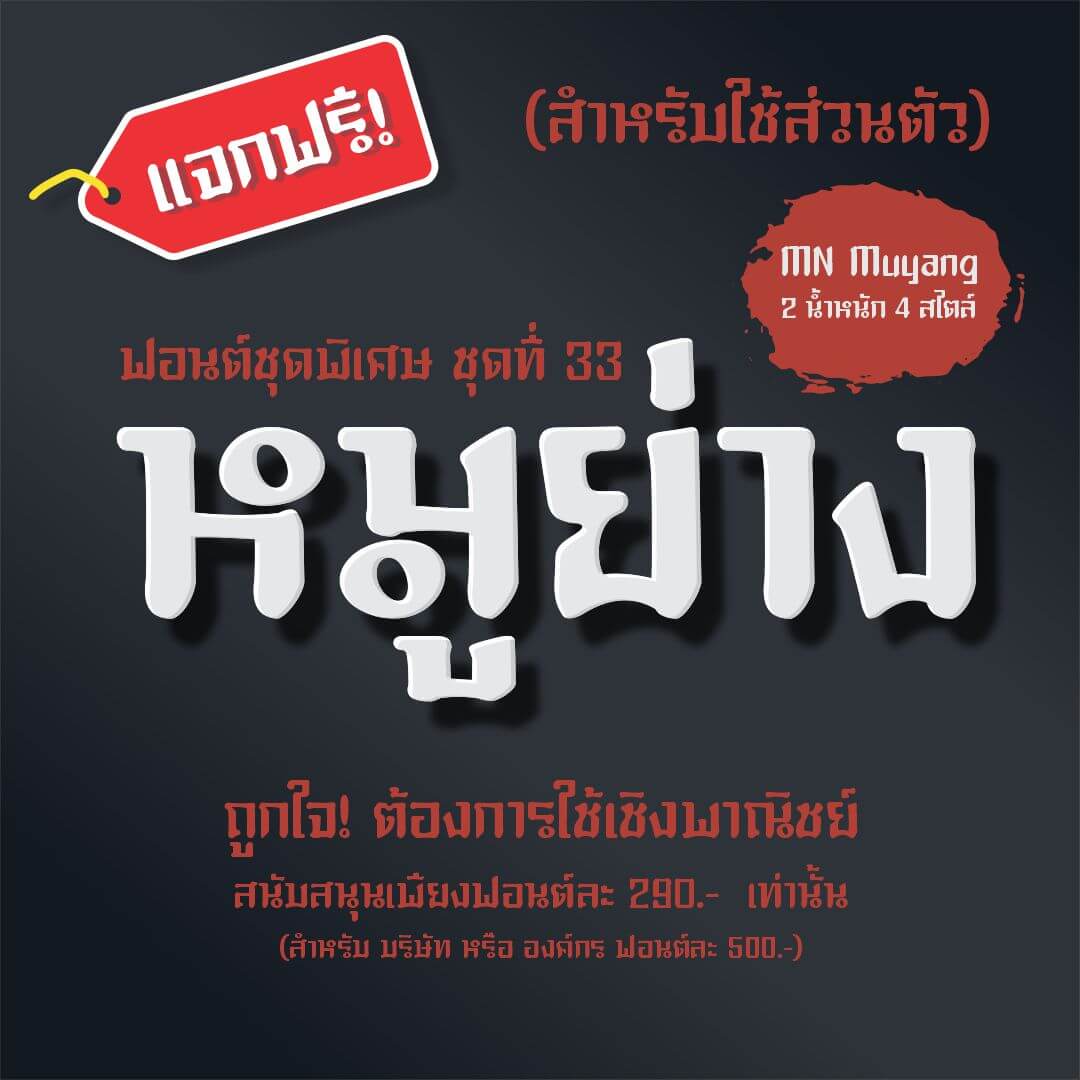
2. เสี่ยวหลงเปา (MN XIAO LONG PAO)
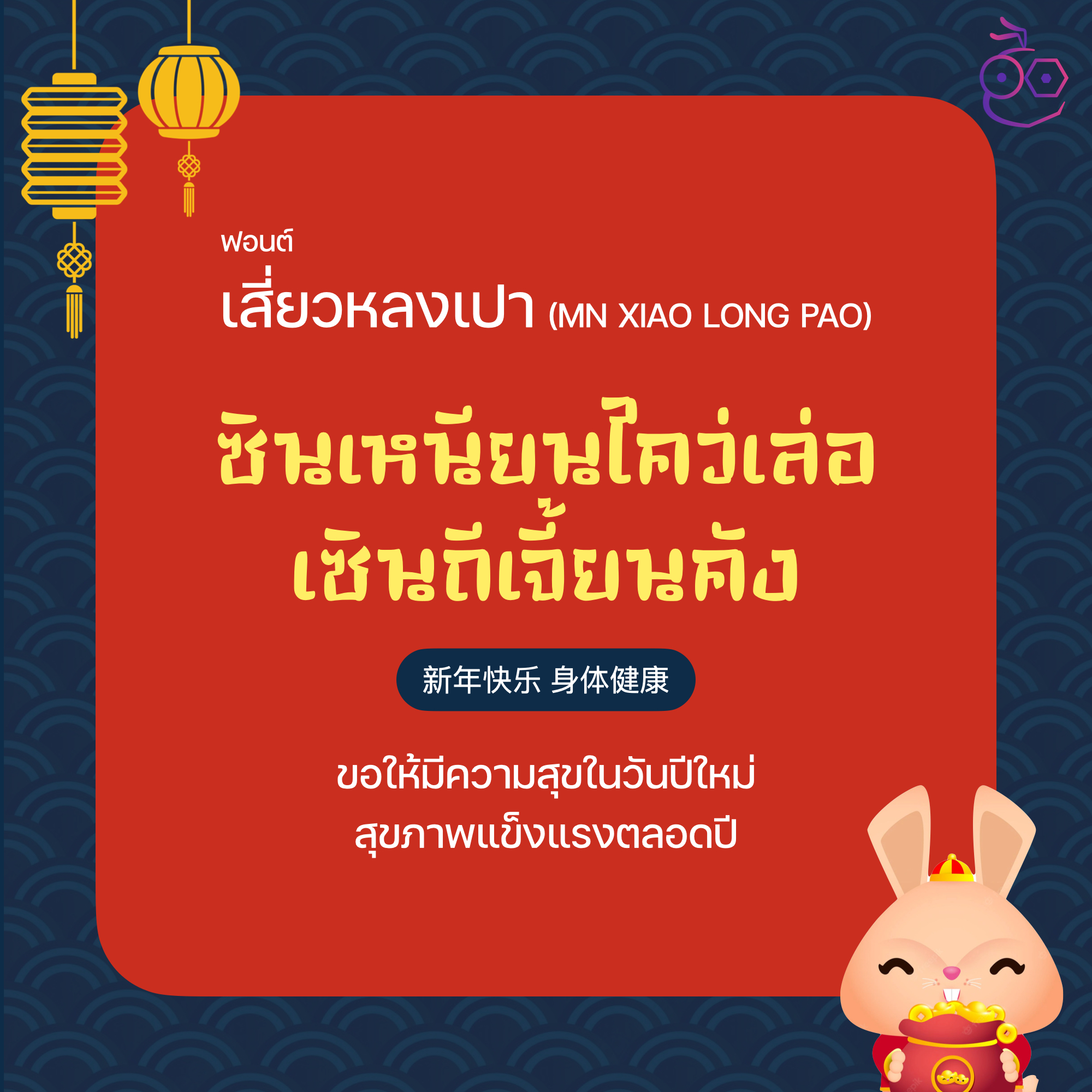
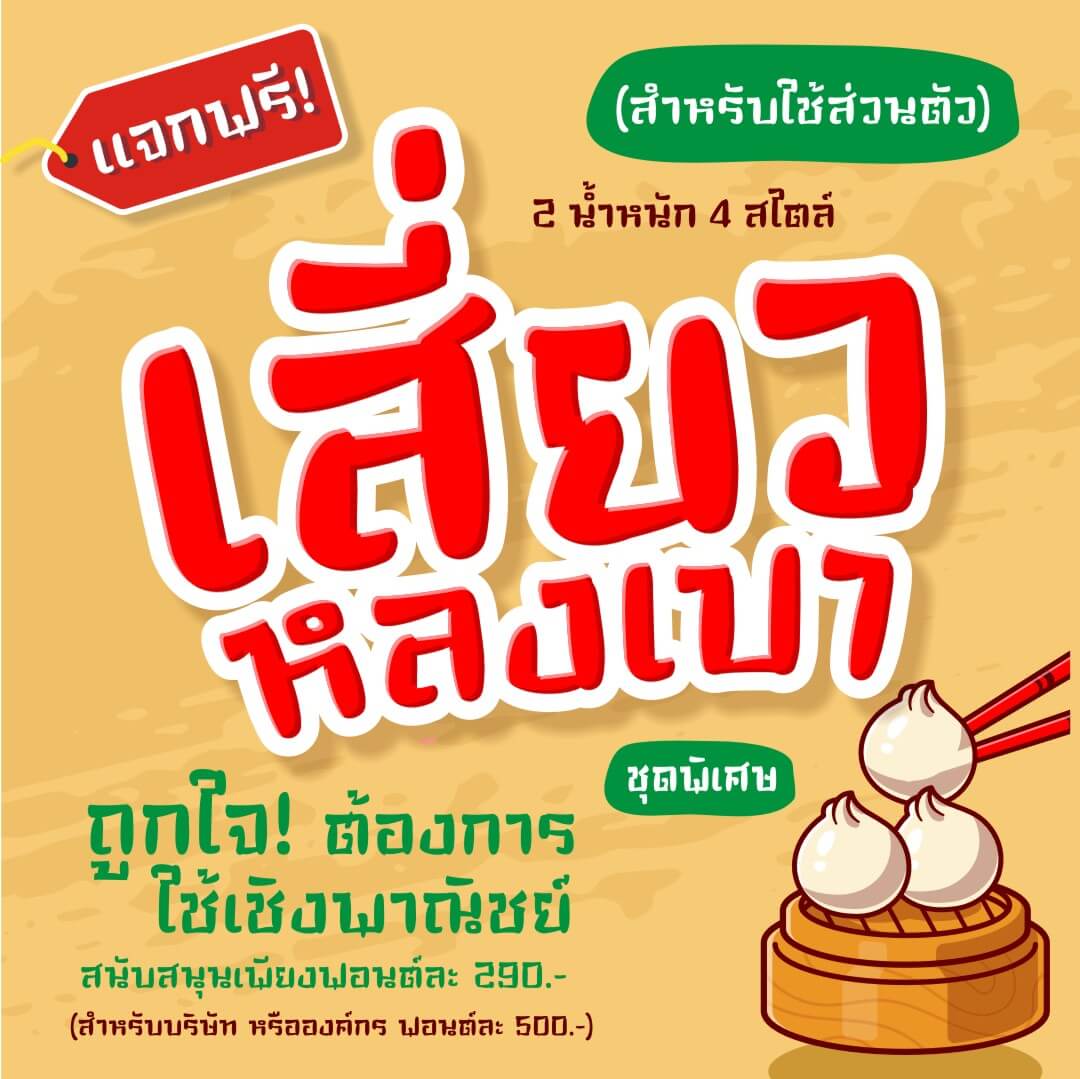
3. ติ่มซำ (Dimsum)
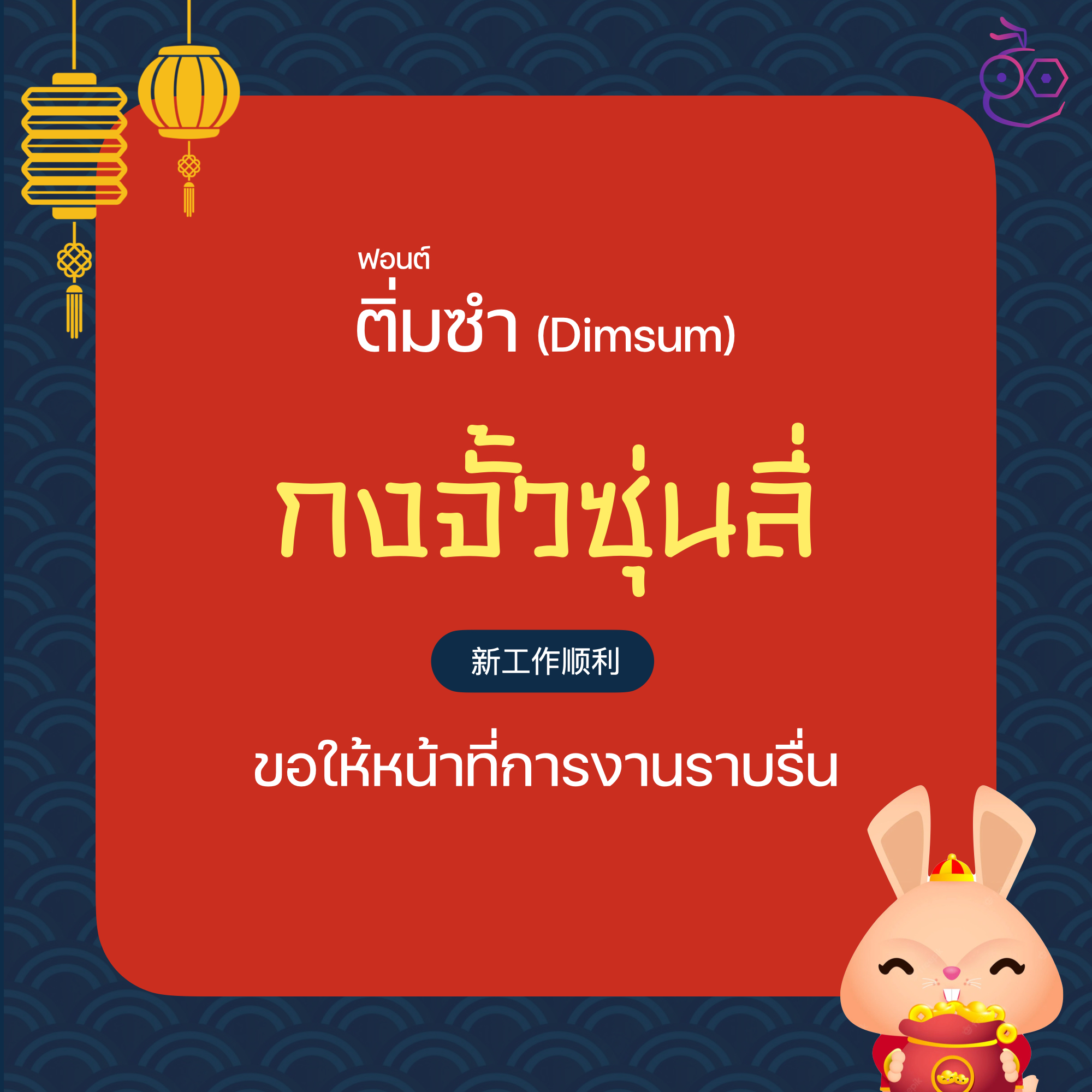
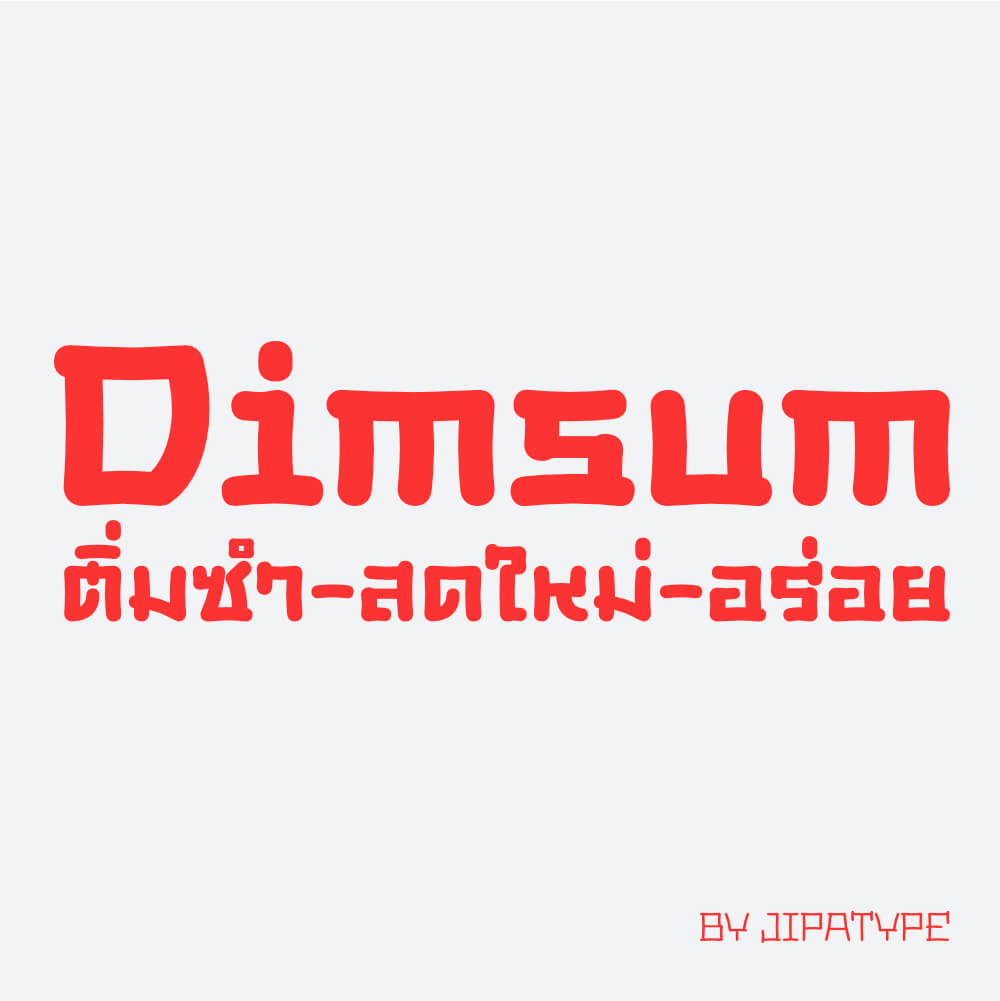
4. ฟอนต์ซาลาเปา
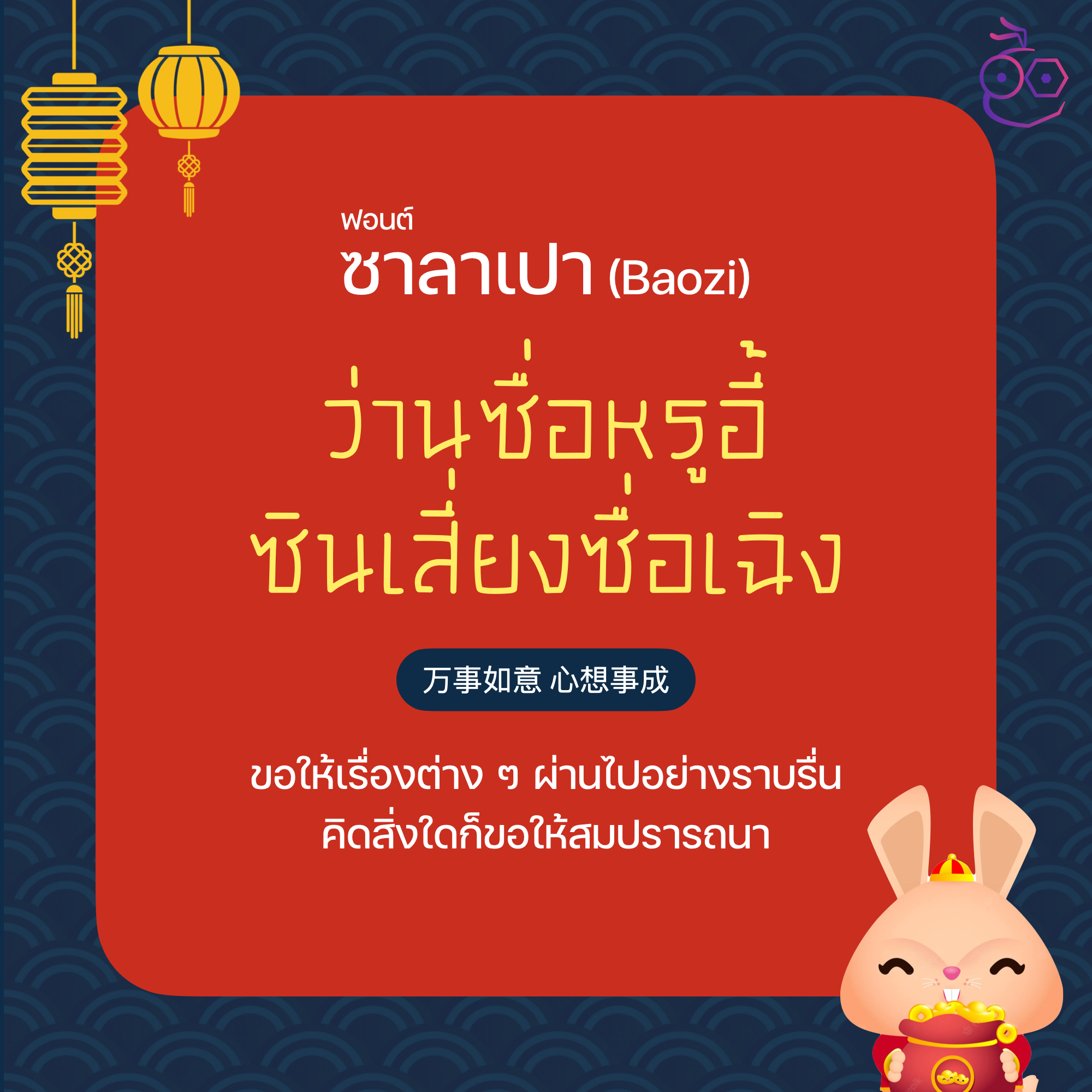
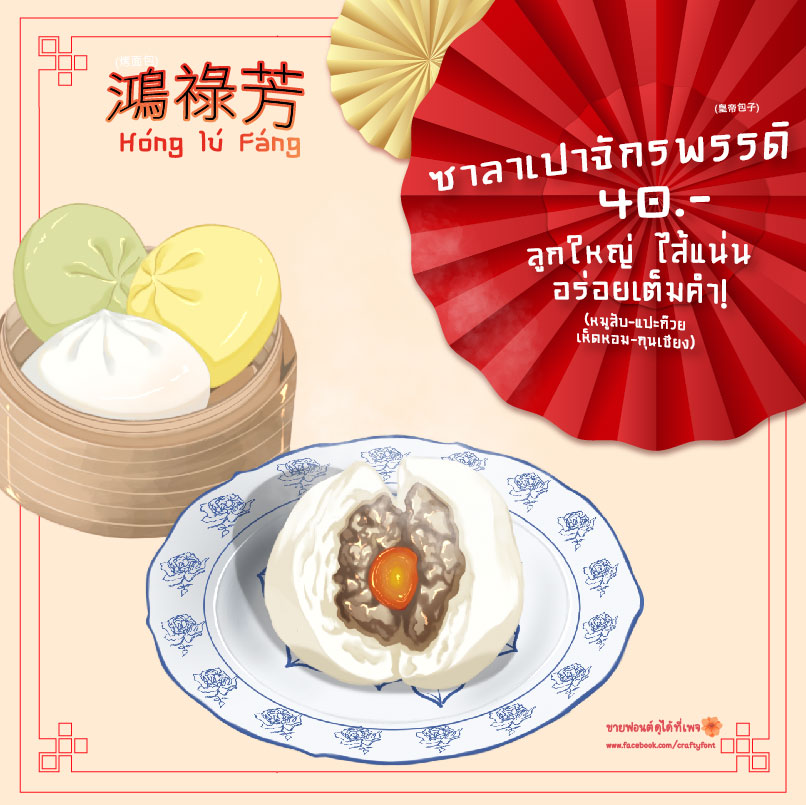
5. LYF_Mulan
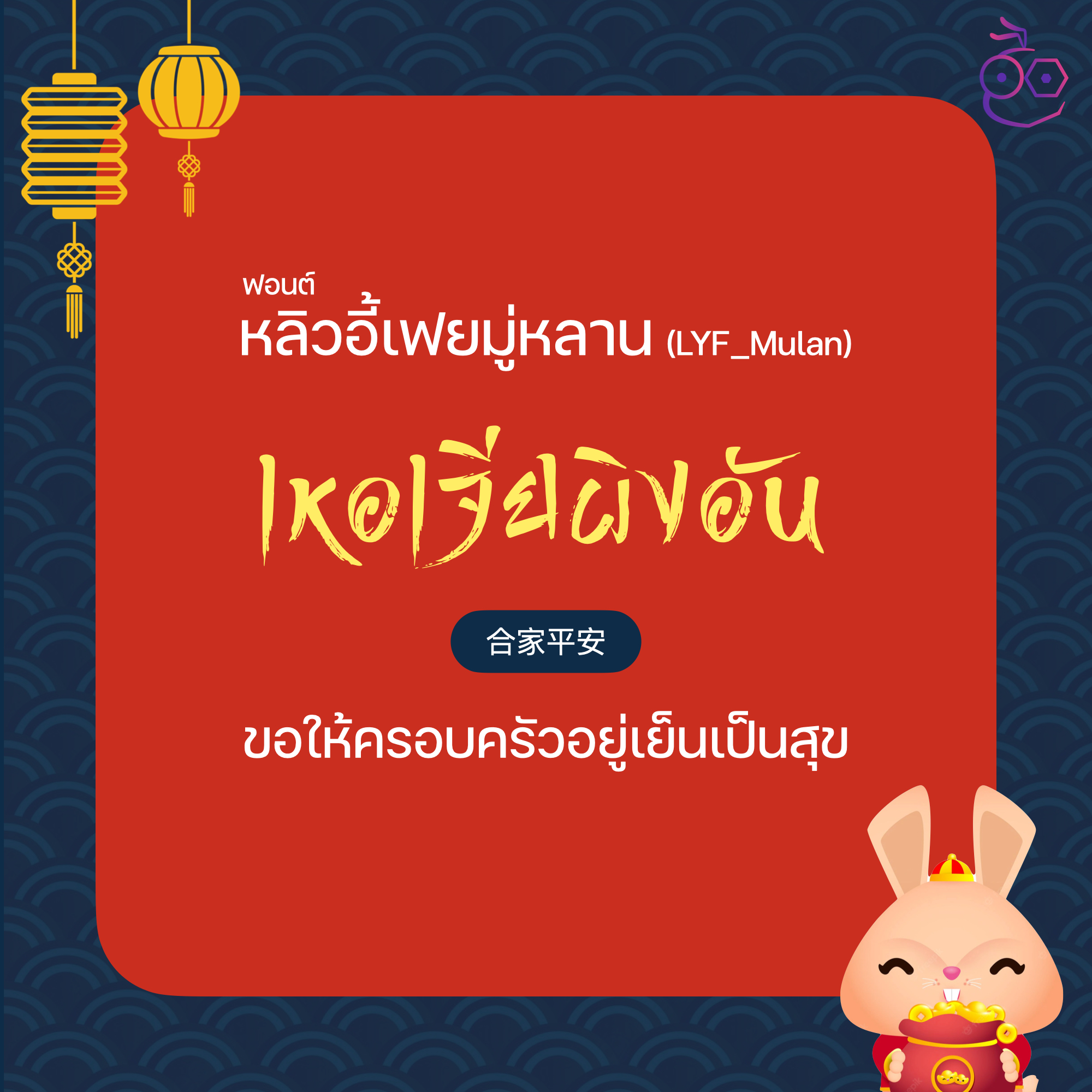
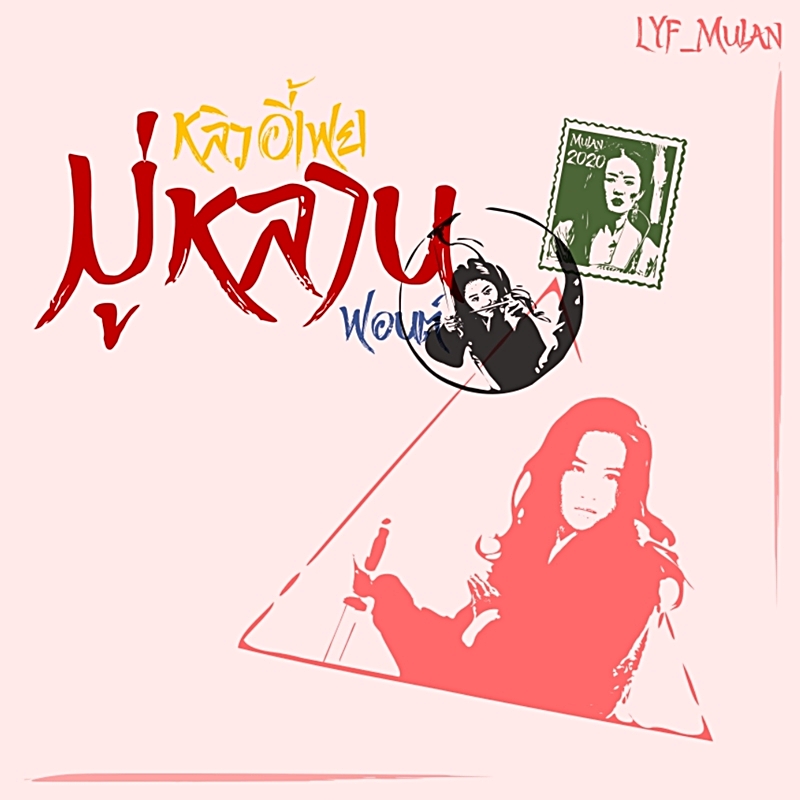
6. j.devilfont@Thai Kek (ไท่เก๊ก)
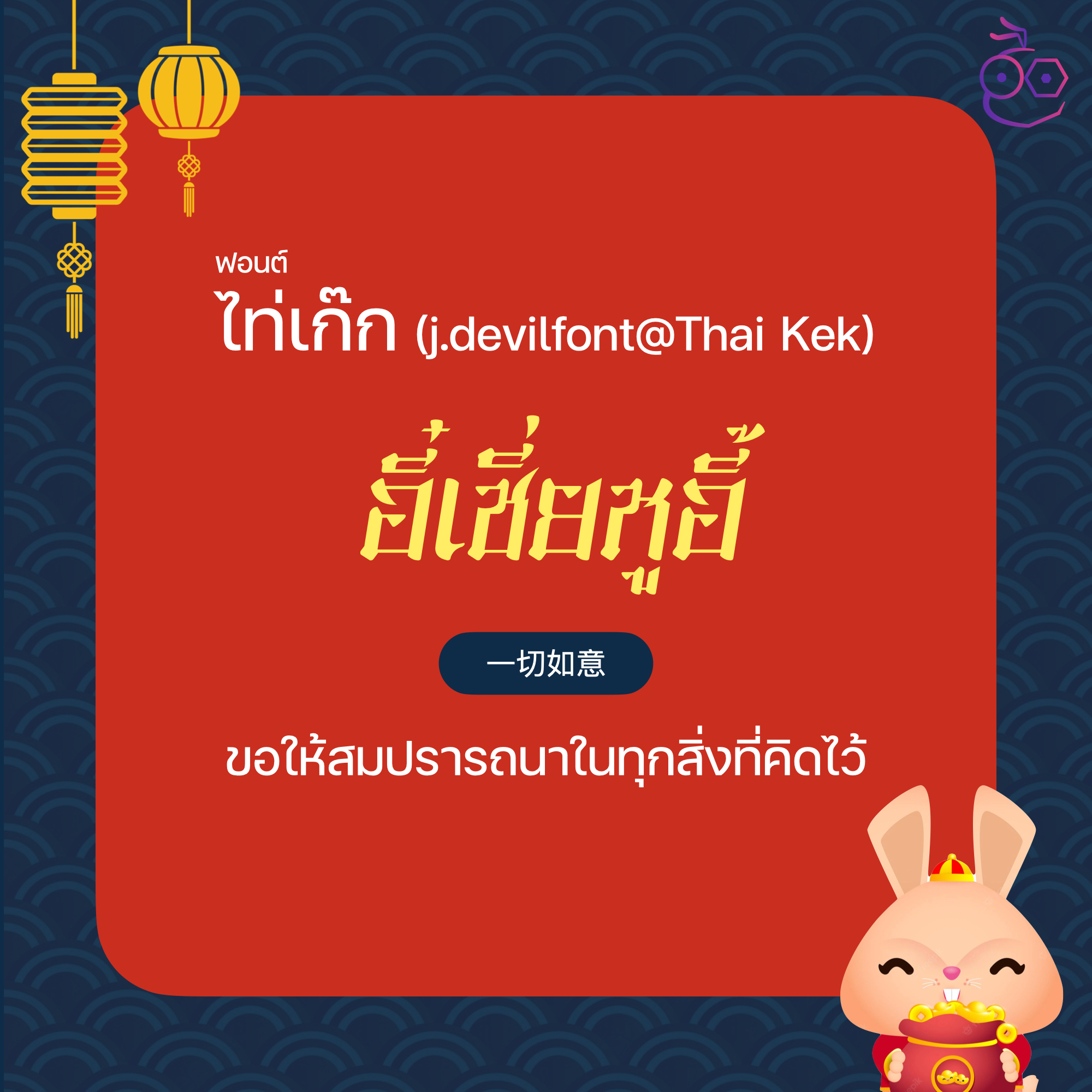
7. LYF_หนังรัก (LYF_LoveFilm)
8. ตรา (SOV_tra)
9. อาณาจักร์ (Anachak)